Lo stile di scrittura gioca un ruolo fondamentale nella stesura di un ottimo manga, per dar vita a storie e personaggi coinvolgenti. Vediamo insieme quali sono i migliori font manga.
Cosa deve avere un font manga
Nel mondo dei manga i caratteri tipografici giocano un ruolo fondamentale, per creare atmosfera ed esprimere il senso della storia.
Scegliere il font giusto è fondamentale per creare la giusta atmosfera, restando in linea con la storia. Ad esempio, un font giovane e gioioso è perfetto per un manga leggero e divertente, mentre un carattere più duro e spigoloso crea tensione nei momenti più cruciali della storia.
Un buon font manga deve avere forme e stili audaci, con linee spesse che richiamo l’attenzione del lettore. Essi devono essere di grande impatto visivo, ma devono anche essere di facile leggibilità.
Ovviamente, molto dipende anche dal genere di storia che stiamo raccontando. Il carattere deve essere sempre in linea con la storia.
Diverse tipologie di font manga
Nello stesso testo possiamo trovare caratteri tipografici diversi tra di loro. A seconda dell’utilizzo che dobbiamo farne possiamo scegliere il font migliore per le nostre esigenze.
I font per il dialogo e la narrazione devono essere facilmente leggibili. Le linee sono spesse e arrotondante. Delle leggere sfumature nei caratteri tipografici indicano anche emozioni. Ad esempio, un font con angoli più spigolosi e inclinato può esprimere uno stato d’ansia, mentre un carattere più morbido esprime tranquillità.
Alcuni caratteri sono puramente decorativi e vengono utilizzati per i titoli, i nomi o gli effetti sonori.
I migliori: Anime Ace
Uno dei caratteri più utilizzati è Anime Ace, un carattere vivace, molto leggibile, gioioso e giovanile. Perfetto per le storie più leggere e divertenti e per i manga per bambini e ragazzi.
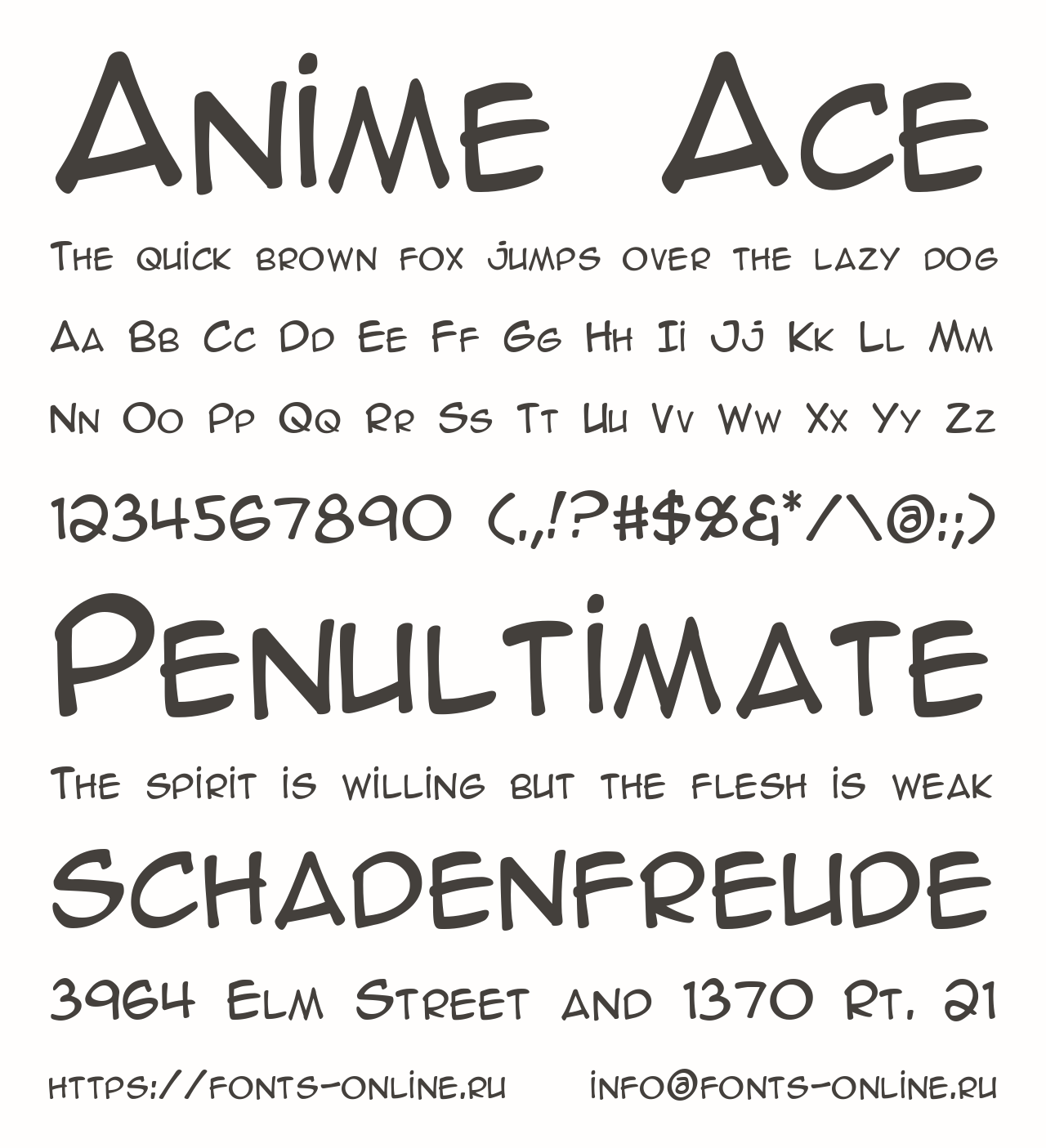
I migliori: Mangaka
È un carattere leggibile e lineare, molto semplice, elegante e raffinato. Viene utilizzato per dialoghi e didascalie di storie romantica o drammatiche.
I migliori font manga: Outrun Future
È un carattere futuristico e particolare che non può essere utilizzato per qualsiasi tipo di narrazione. Le lettere sembrano essere in movimento ed è perfetto per le storie di fantascienza.
Questo font difficilmente viene utilizzato per il corpo principale del testo, ma è perfetto per i titoli o le scene più coinvolgenti.
I migliori: Mabook
È un font giocoso e in movimento, morbido e leggero. Perfetto per le storie più leggere, divertenti, per scene comiche e momenti narrativi più spensierati.
I migliori: Adventure
È un carattere accattivante, audace e avventuroso. Le lettere sono spesse e robuste, energiche e in movimento, perfette per catturare l’attenzione del lettore.
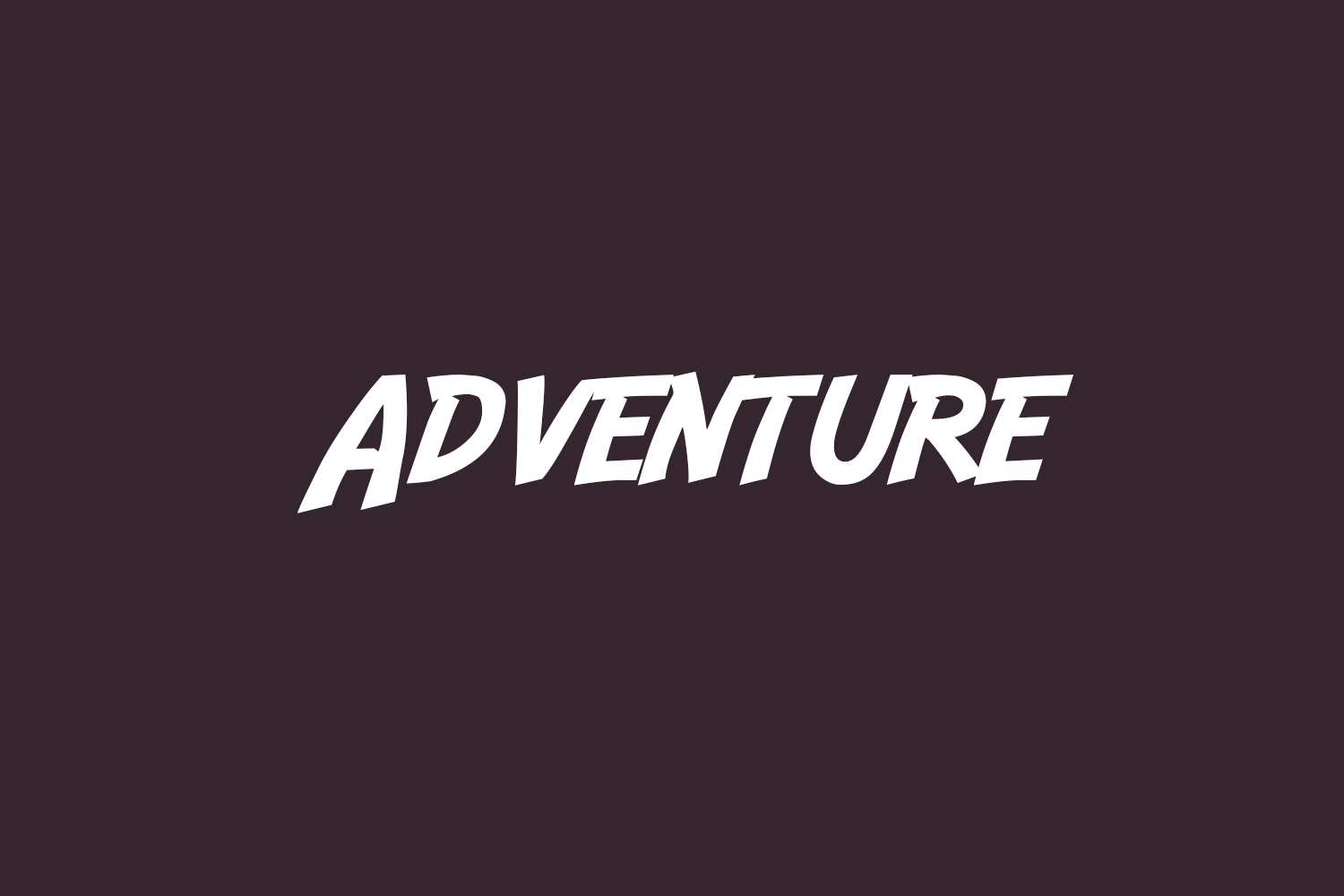
Questo font viene utilizzato per storie d’azione o momenti d’esplorazione.
Otaku Rant Anime Font Family
Questo non è un singolo carattere, ma una famiglia di font pensata appositamente per la scrittura degli anime.
Questa famiglia è composta da tre tipi di caratteri: regolare, corsivo e grassetto. È un carattere semplice, elegante e di facile leggibilità.
I migliori font anime: Anime Inept
Questo carattere richiama la scrittura a mano, è semplice ed elegante, perfetto per dare un tocco di personalità al testo.
I migliori: Japan Daisuki
Questo font è geometrico e moderno. Le linee sono chiare e dure, perfetta per conferire un senso di confidenza e sicurezza.
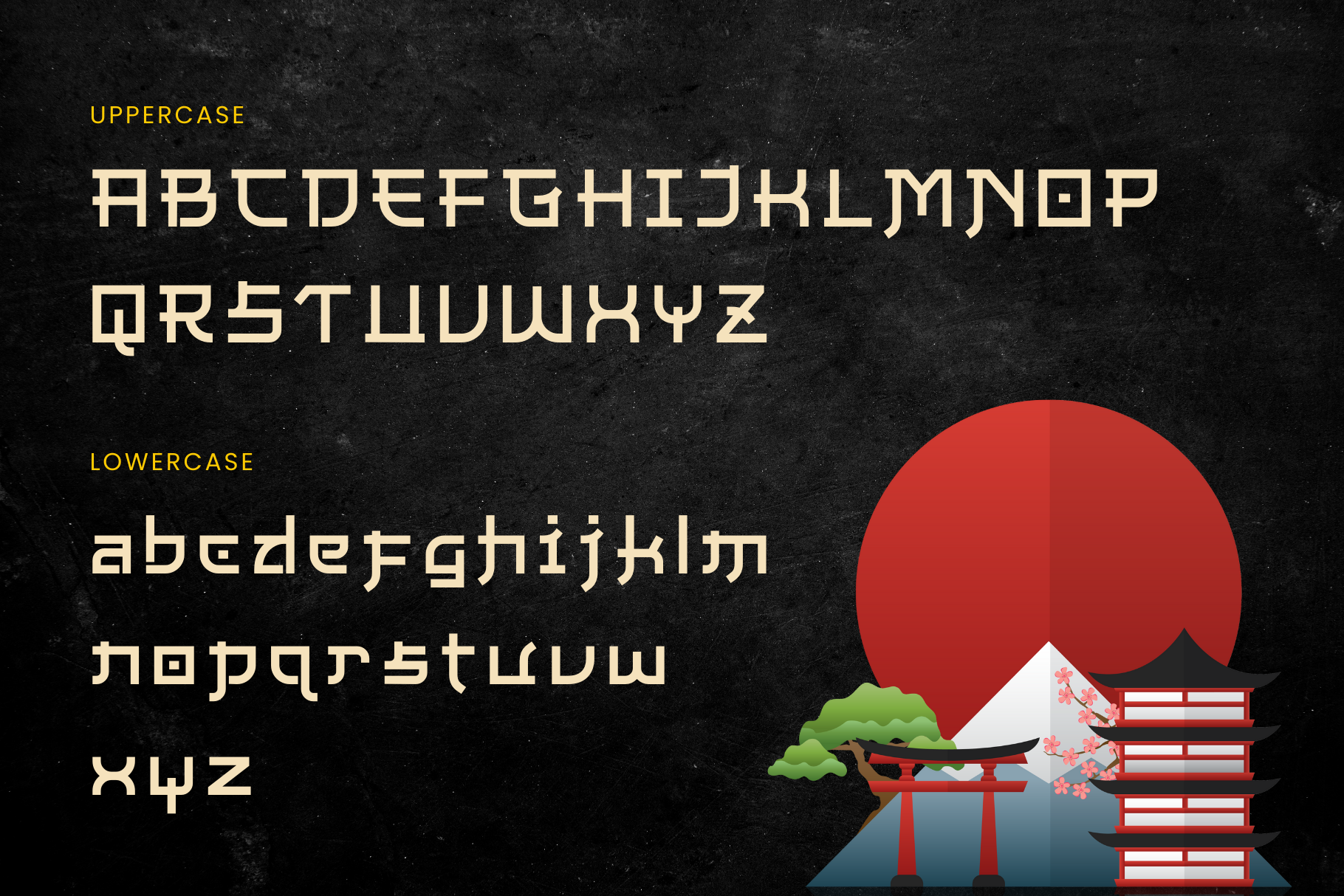
È un carattere che strizza l’occhio all’oriente, con un tocco di giocosità e dinamismo.